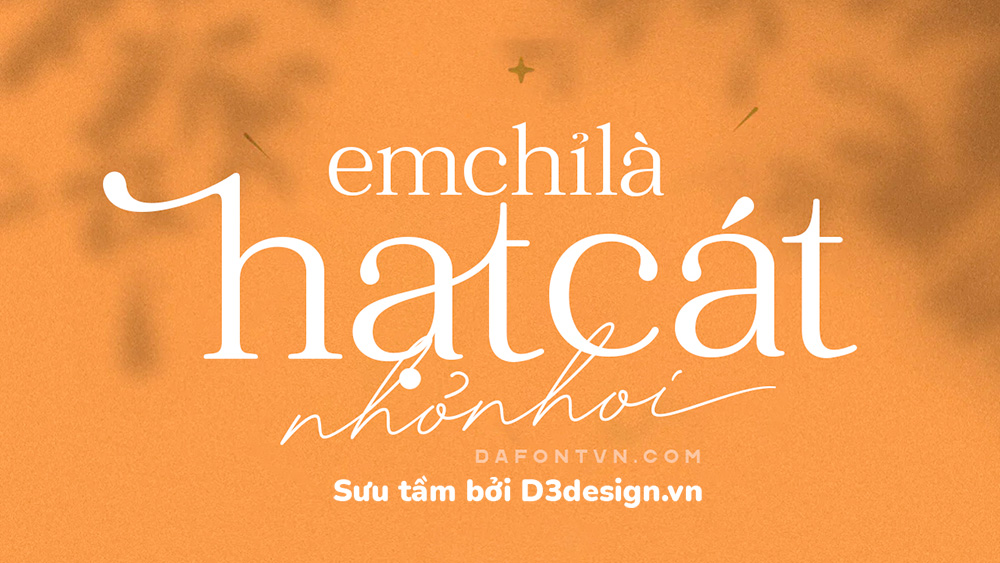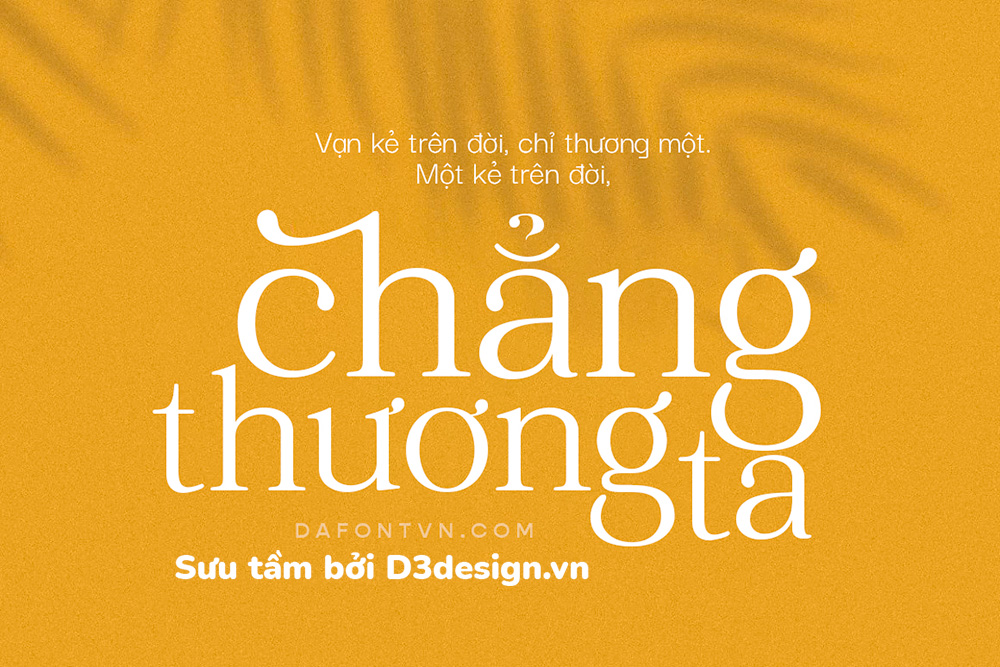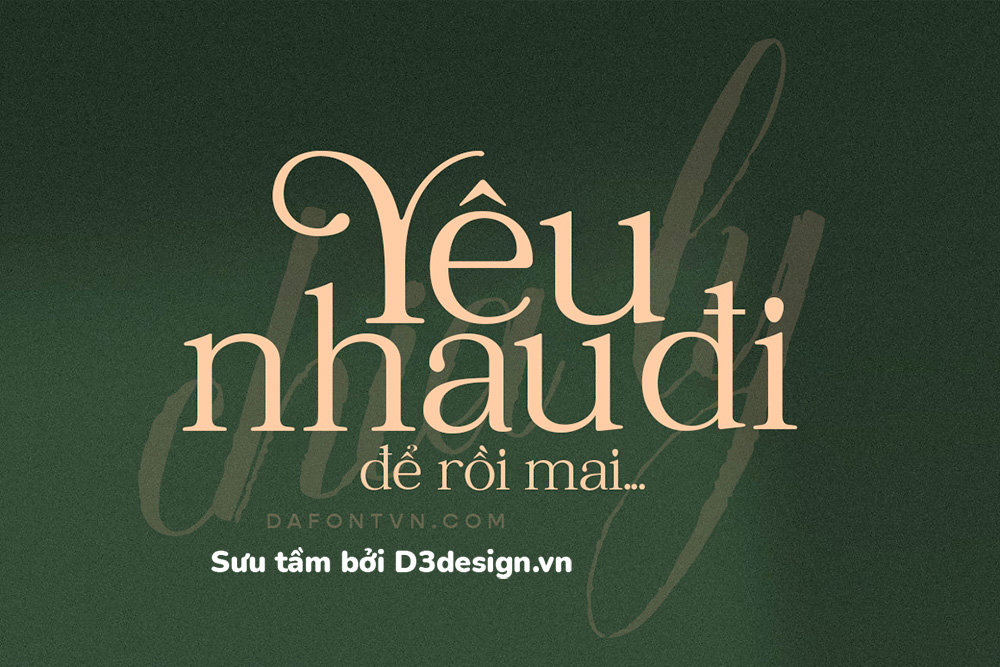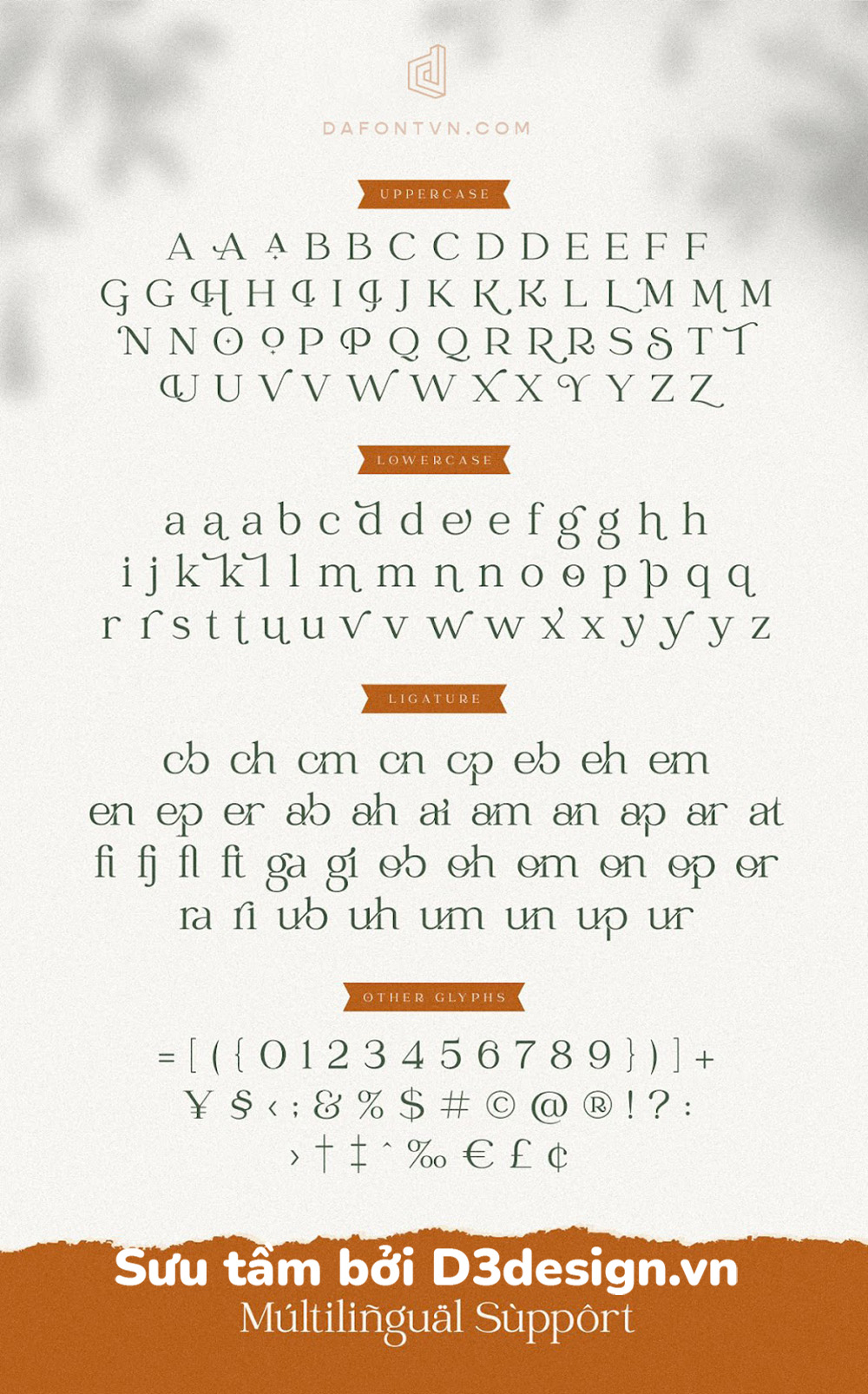
Font Việt Hóa - Catchy Mager Mang Phong Cách Thanh Lịch Và Hiện Đại
Catchy Mager Font là một kiểu phông chữ độc đáo và hiện đại phù hợp cho hầu hất các thiết kế của bạn.
Dựa trên những thiết kế hiện đại tác giả đã cho ra đời 1 kiểu font thanh lịch và độc đáo hoàn hảo cho xây dựng thương hiệu và thiết kế logo, cũng như cho bất kỳ thiết kế nào cần 1 font chữ hiển thị tốt, đẹp mắt và sang trọng. Font bao gồm 1 số glyph ấn tượng và một số chữ ghép để bạn có thể tạo ra các tác phẩm độc đáo hơn.
Font Catchy Mager việt hóa đầy đủ, kerning, mã hóa PUA để sử dụng dễ dàng trên bất kỳ phần mềm nào. Ngoài ra, vì font gốc 1 số ký tự và dấu chưa được tối ưu cho lắm nên mình đã chỉnh sửa lại để hoàn thiện hơn.